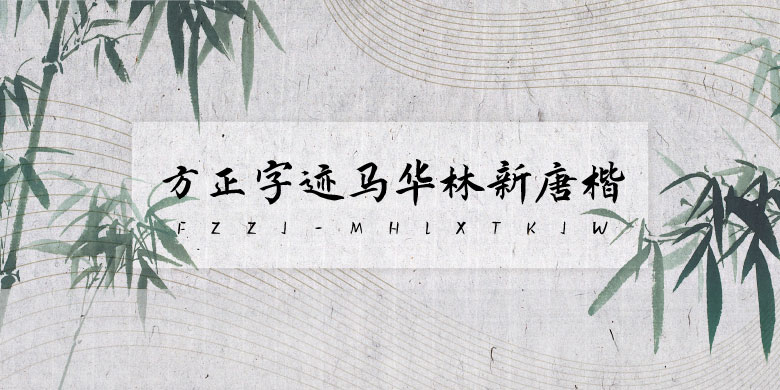
方正字迹-马华林新唐楷
方正字迹-马华林新唐楷:综合唐楷颜柳欧褚和赵字的共性为基架,创作出有别于上述诸家的新古典主义楷书。 结构于端庄寓奇侧,用笔以严谨显灵动,避免僵滞刻板,追求潇洒通畅。 创意上增强古意,丰富笔法,力避匠气,体现变化。为使笔画更多骨力丶更富姿态丶更使丰满`更显变化,适当的融入北碑元素。 该字体不仅适合于普通排版,还可用于各种碑板的刻写和书刊题名及商家企业的匾牌用字所需。
作者马华林,中国书法家协会会员,其《唐诗六十首》等三部楷书字帖被全国社会美术水平考级中心选为考级用书。2009年在全国人大会议中心被授于“中国书画:非物质文化遗产功勋人物”称号。